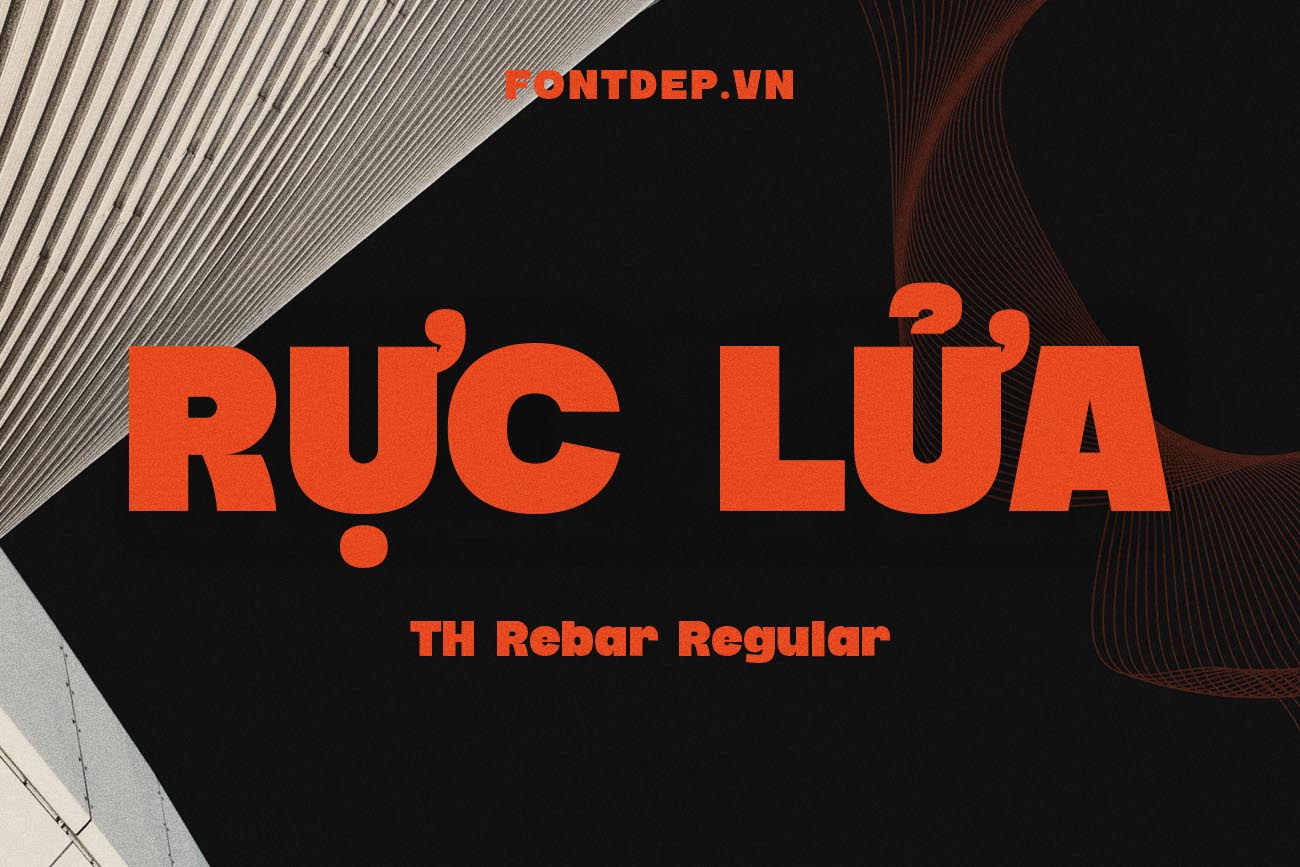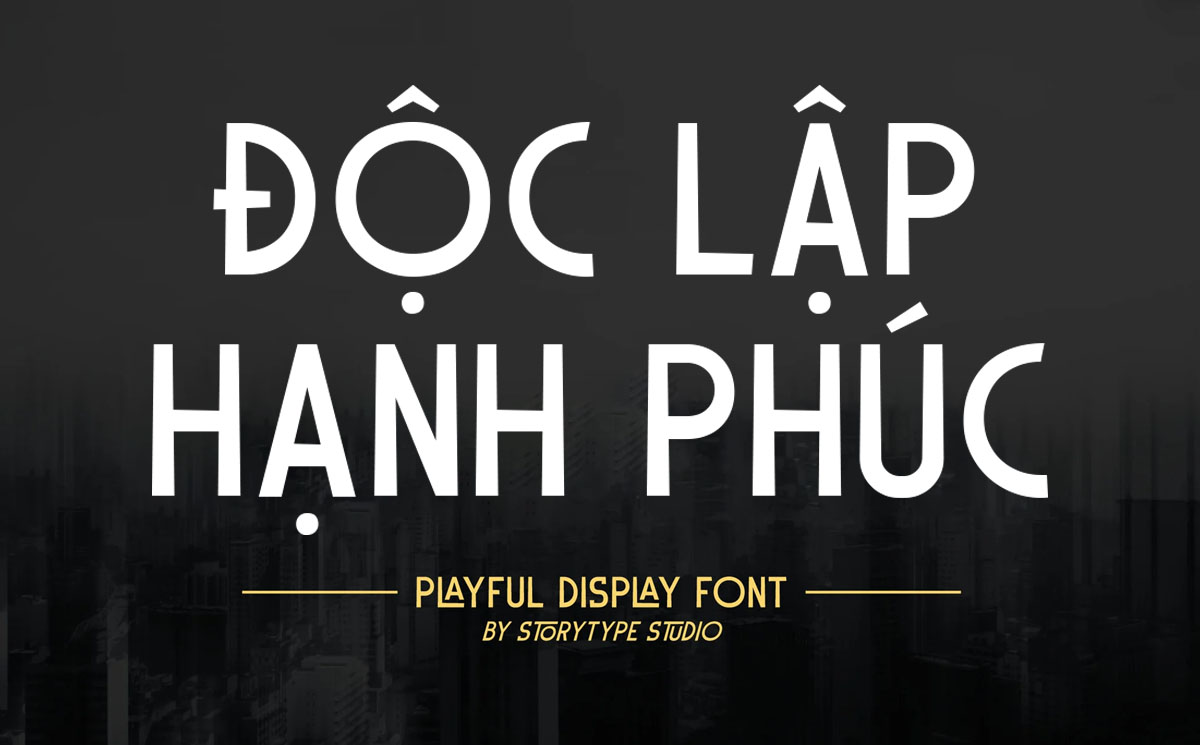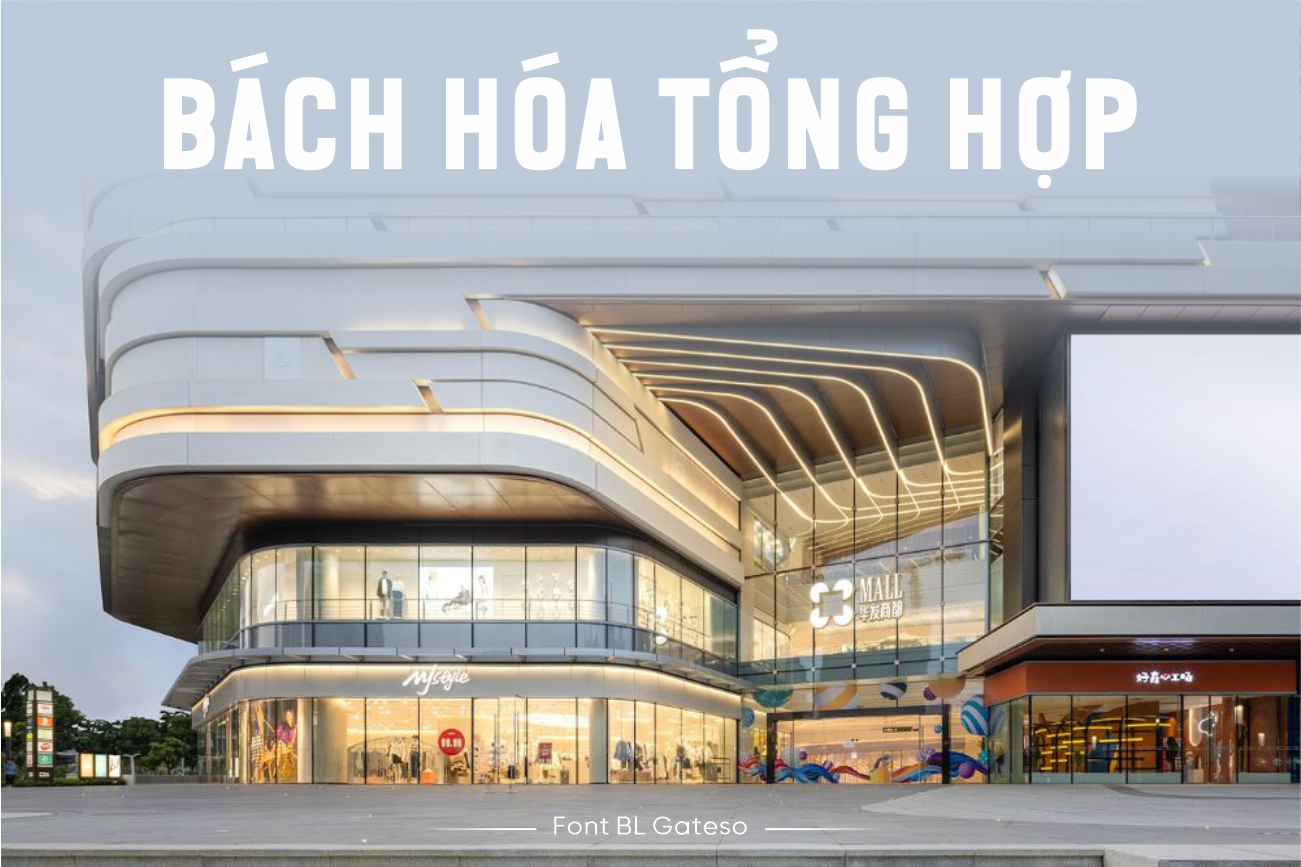
Font chữ đẹp cho Canva: gợi ý font Việt hóa dễ dùng trong thiết kế online
Gợi ý các font chữ đẹp cho Canva, dễ dùng trong thiết kế online như bài social, poster sale, thumbnail, menu, banner sự kiện và nhận diện thương hiệu.
Canva giúp việc thiết kế nhanh hơn rất nhiều: kéo thả, chọn template, đổi ảnh, chỉnh màu và xuất file chỉ trong vài phút. Nhưng nếu phần chữ chưa đẹp, thiết kế vẫn dễ bị "mẫu có sẵn", thiếu điểm nhấn hoặc khó đọc. Với người làm social media, bán hàng online, giáo viên, chủ shop nhỏ, creator hay designer làm nhanh nội dung cho khách, chọn đúng font chữ đẹp cho Canva là bước rất quan trọng.
Vấn đề thường gặp là nhiều font nhìn đẹp trong preview tiếng Anh nhưng khi gõ tiếng Việt lại lỗi dấu, lệch dấu hoặc mất cảm giác cân đối. Vì vậy, nếu thiết kế hướng đến khách hàng Việt Nam, bạn nên ưu tiên font Canva Việt hóa, đặc biệt là các font có dấu rõ, đọc tốt ở kích thước nhỏ và dễ phối với template có sẵn.
Bài viết này gợi ý các nhóm font Việt hóa dễ dùng trong Canva, kèm cách chọn font cho từng kiểu thiết kế online như poster sale, thumbnail, menu, bài đăng social, quote, banner sự kiện và thương hiệu cá nhân.
Vì sao nên dùng font Việt hóa khi thiết kế trên Canva?
Tránh lỗi dấu tiếng Việt
Canva có nhiều font đẹp, nhưng không phải font nào cũng hỗ trợ tiếng Việt tốt. Khi gõ các chữ như "khuyến mãi", "trọn bộ", "mỹ phẩm", "đặc biệt", "giảm giá", nhiều font có thể lỗi dấu hoặc làm dấu chạm vào nét chữ. Với thiết kế bán hàng, lỗi dấu khiến ấn phẩm kém chuyên nghiệp ngay lập tức.
Font Việt hóa giúp bạn kiểm soát tốt hơn phần chữ tiếng Việt. Dấu được xử lý đồng bộ với bộ chữ, giúp tiêu đề, mô tả và thông tin phụ rõ ràng hơn.
Tạo khác biệt so với template phổ thông
Nếu ai cũng dùng các font mặc định quen thuộc, thiết kế Canva rất dễ giống nhau. Khi bạn cài thêm font Việt hóa riêng, cùng một template có thể trông khác hẳn: cá tính hơn, đúng ngành hơn và có cảm giác thương hiệu hơn.
Dễ xây dựng bộ nhận diện cho shop nhỏ
Một shop online có thể chọn 2 đến 3 font cố định: một font tiêu đề, một font nội dung, một font nhấn. Khi dùng lặp lại trên poster, story, menu, banner và catalogue, thương hiệu sẽ nhất quán hơn mà không cần thiết kế quá phức tạp.
Cách chọn font đẹp cho Canva theo mục đích
Font cho poster sale cần nổi bật
Poster sale cần chữ to, rõ và có lực. Các cụm như "Flash Sale", "Giảm 50%", "Mua 1 tặng 1" phải đọc được trong vài giây. Nên chọn font dày, chắc, ít chi tiết và có độ tương phản tốt với nền.
Font cho bài social cần dễ đọc
Bài social thường xem trên điện thoại, nên chữ phải rõ ở kích thước nhỏ. Đừng chọn font quá uốn lượn cho toàn bộ nội dung. Font script hoặc viết tay chỉ nên dùng cho một câu ngắn; phần mô tả nên dùng sans-serif.
Font cho thumbnail cần cá tính
Thumbnail YouTube, Reels, TikTok hoặc khóa học online cần chữ mạnh, dễ nhìn và khác biệt. Font display, font thể thao, font công nghệ hoặc font bo tròn có thể giúp thumbnail nổi hơn.
Font cho menu và bảng giá cần gọn
Menu, bảng giá, voucher và catalogue cần đọc nhanh. Hãy ưu tiên font sans-serif gọn, có đủ weight, dấu tiếng Việt rõ. Font quá trang trí sẽ làm khách khó đọc thông tin sản phẩm.
Gợi ý font Canva Việt hóa dễ dùng
1. TH Glafty
TH Glafty hợp với thiết kế Canva cần sự vui tươi, trẻ trung và năng động. Font này phù hợp cho poster lớp học, bài social bán hàng, banner mini game, nội dung trẻ em hoặc các thương hiệu có tính cách thân thiện.
Bạn có thể dùng TH Glafty cho tiêu đề chính, sau đó phối với một font sans-serif gọn cho mô tả. Cách này giúp bài đăng nổi bật nhưng vẫn dễ đọc.
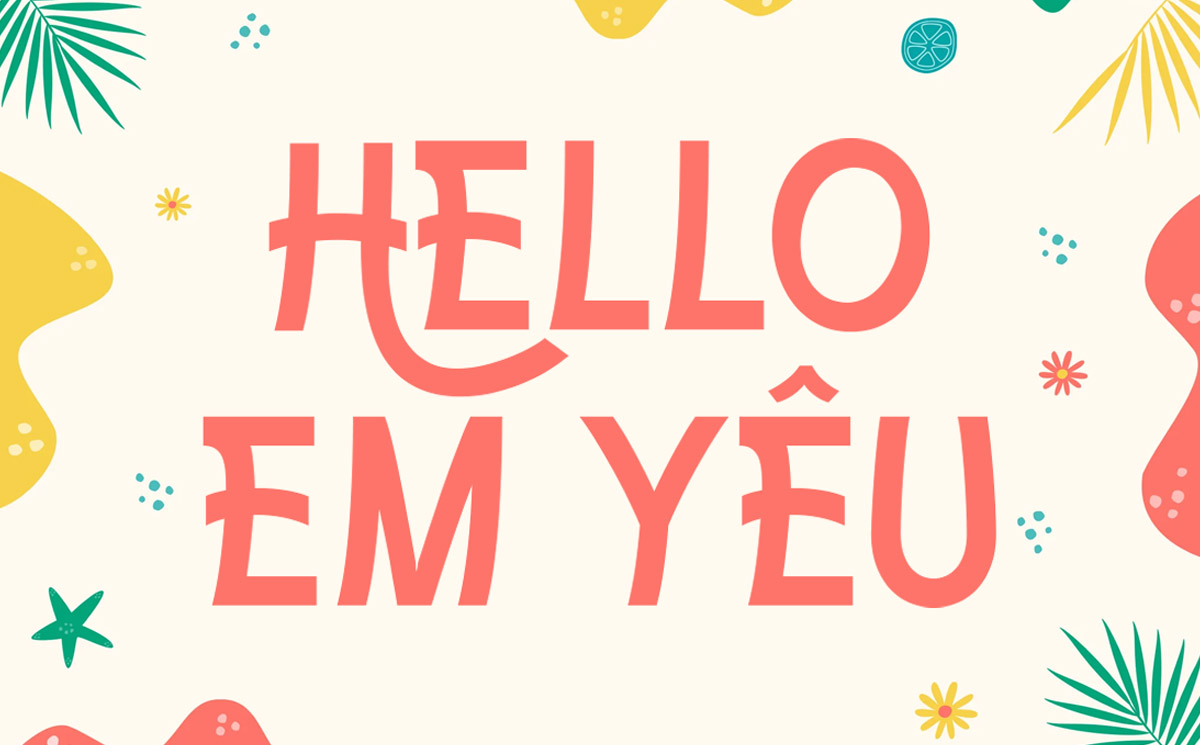
2. TH Playful Bubble
TH Playful Bubble là lựa chọn rất hợp cho thiết kế cute, vui nhộn, đồ ăn vặt, lớp học thiếu nhi, sản phẩm mẹ và bé hoặc sticker social. Dáng chữ bo tròn giúp thiết kế có cảm giác gần gũi và đáng yêu.
Font này nên dùng cho chữ ngắn, tiêu đề hoặc nhãn nổi bật. Nếu dùng quá nhiều trong một layout, thiết kế dễ bị nặng và thiếu khoảng thở.
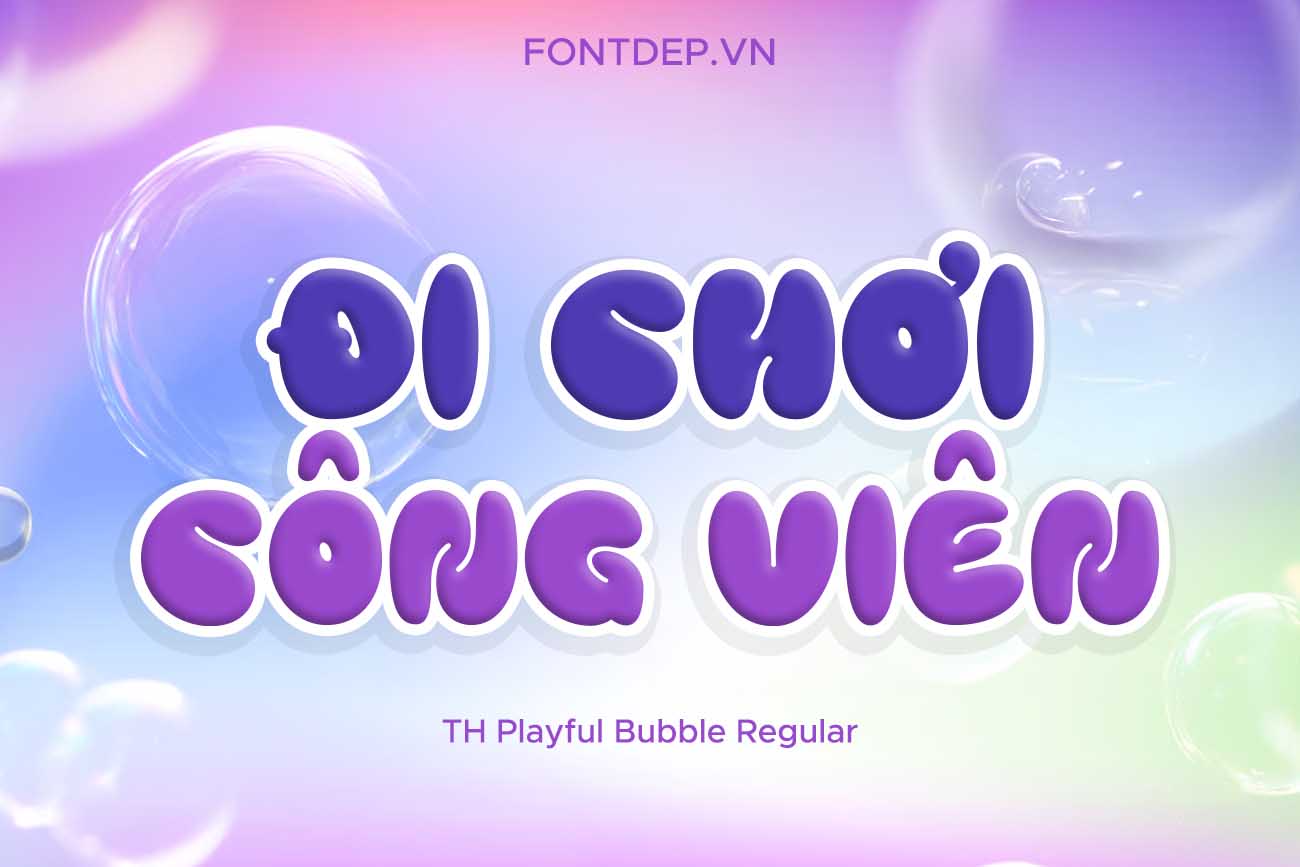
3. TH Yomogi Regular
TH Yomogi Regular có cảm giác cute và mềm hơn các font display dày. Font phù hợp với bài quote nhẹ nhàng, postcard, giáo dục, nội dung lifestyle hoặc các template Canva có màu pastel.
Nếu thiết kế của bạn cần sự dễ thương nhưng không quá ồn ào, TH Yomogi Regular là lựa chọn đáng thử. Hãy dùng màu chữ dịu, nền sáng và khoảng cách dòng thoáng.
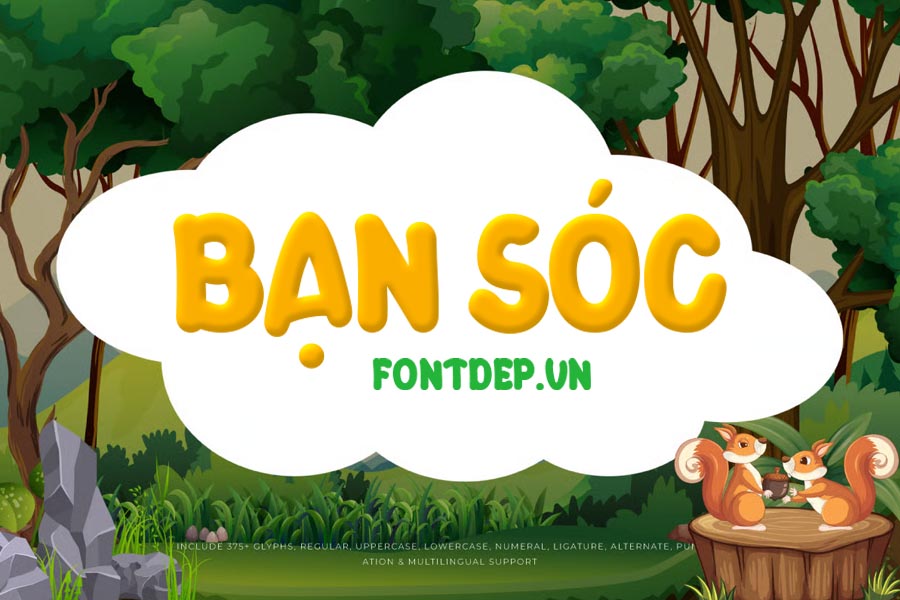
4. TH Bagyo Sans
TH Bagyo Sans phù hợp cho thiết kế trẻ em, khóa học, poster workshop, đồ chơi, sách thiếu nhi hoặc bài đăng cần cảm giác thân thiện. Dáng chữ bo tròn giúp font dễ gần hơn các sans-serif cứng.
Trong Canva, bạn có thể dùng TH Bagyo Sans cho tiêu đề và nút CTA. Phần thông tin chi tiết nên giữ cỡ chữ vừa phải để bố cục không bị chật.
Khi có một bộ font Việt hóa riêng, thiết kế Canva của bạn sẽ bớt giống mẫu đại trà, đồng thời giữ được sự chuyên nghiệp ở mọi điểm chạm: bài social, story, poster, menu, catalogue, thumbnail và banner quảng cáo.